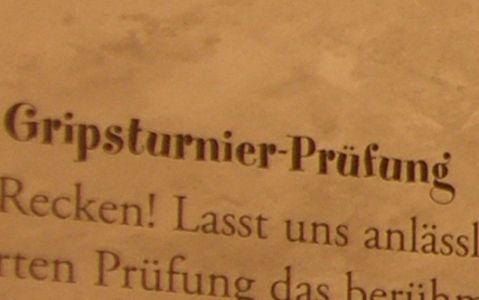
welche schrift ist das?
Ich möchte gerne die Schrift aus der Headline verwenden, habe nur leider null Ahnung, wie sie heißt. Sieht ein bißchen aus als hätte jemand mit der Bodoni gespielt. Kann hier jemand helfen?